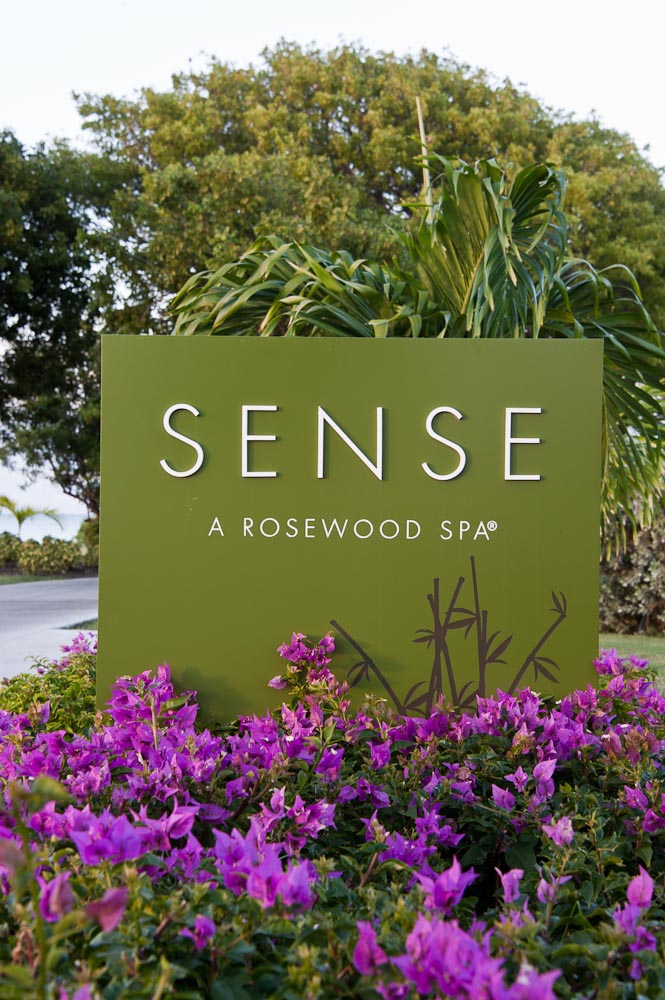
Các thím ơi! font này là font gì ạ [​IMG]
Futura ND Light đó bạn!
Ai có thể việt hóa lại font UVF DK Crayon Crumble được không, font ấy những chữ có 2 dấu tiếng việt đều không viết được, ít nhất là ở máy mình nó bị như vậy
vẫn viết được bình thường mà bạn.
Sử dụng bảng mã Unicode nhé.
Mèo Heo: Mình là translator của 1 nhóm sub Anime, mình dùng font này trong aegisub thì lần nào cũng bị thế, mình luôn để mã unicode để viết thoại mà
Trước mắt là ko thấy bị gì cả.
font này dựa vào chữ viết tay của Frank Wright, nhìn rất là kiến trúc :D
N.P Mình dùng để viét trong eagisub cơ bạn chứ bình thường ở Word với mấy chỗ khác nó vẫn bình thường
ozzott vậy thì soft đó ko hỗ trợ font unicode rồi.
Giống Proshow cũng vậy, cũng ko gõ được tiếng việt với font unicode
Mèo Heo các bộ font khác như UTM, UVN, Vf, SFU và các font UVF khác mình vẫn viết được đều, chỉ có mỗi font đó là bị như vậy
Thế thì chắc gì do cái font, viết ở đâu cũng bthường mà. :v
N.P Thế mình mởi hỏi nhờ làm lại cái font đó -_-
mấy bác cho em hỏi font trên fb là font gì v a. ? font mà fb sử dụng làm mấy cái để hiển thị tên với cmt :)